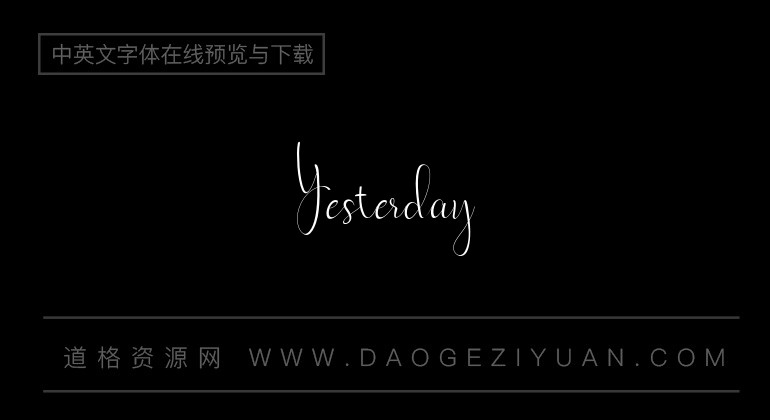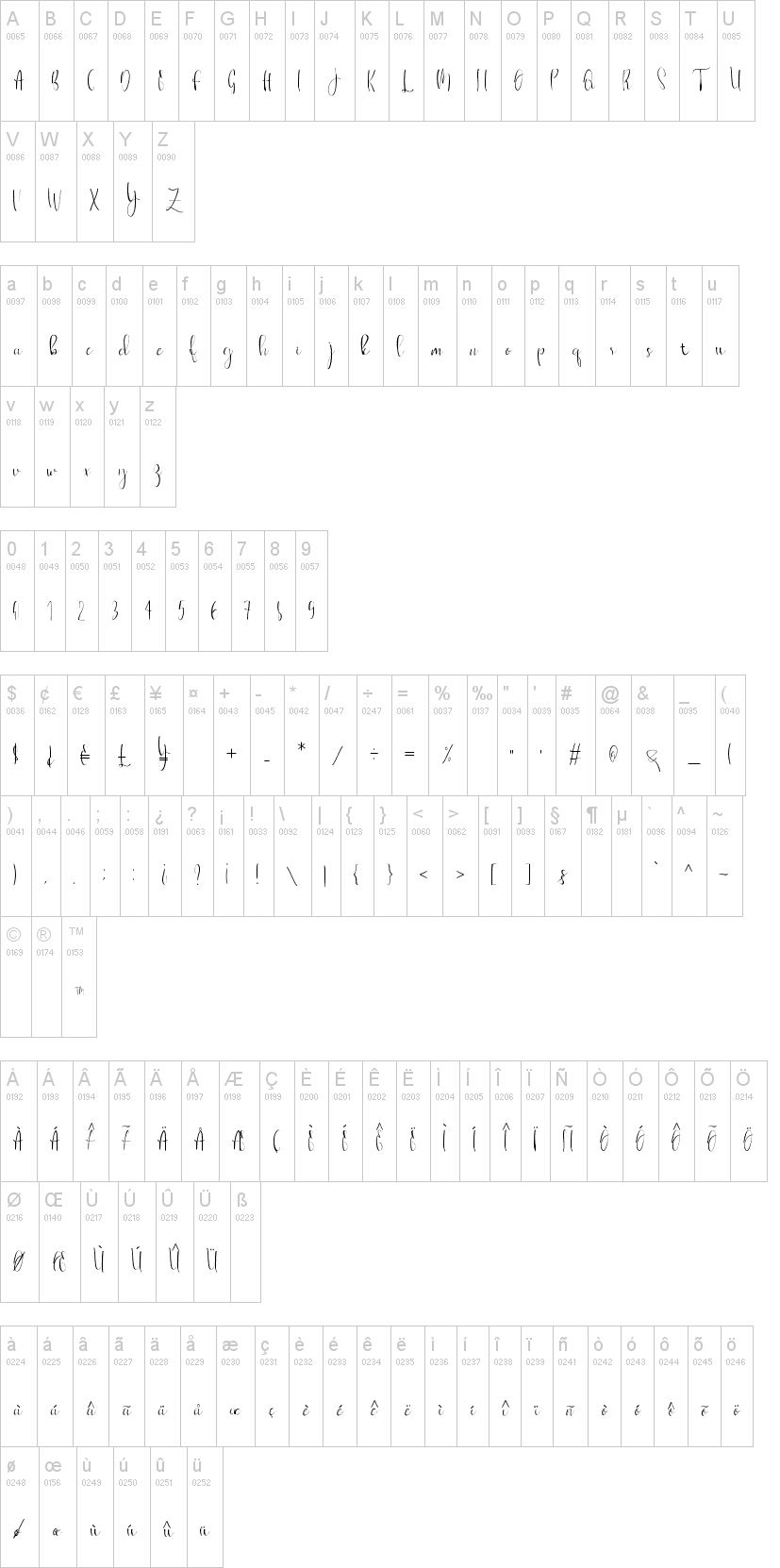
Yesterday
Yesterday 是一款设计师的手写字体,它拥有温暖的感觉,柔和的线条,清晰的字形,以及多变的魅力。它可以用于各种不同的设计,从卡片到海报,从网站到插图,都能够表现出独特的气质。它可以提供有趣的文字效果,也可以用作大胆的标题或句子,以添加更多的惊喜。
Yesterday是一款非常不错的手写艺术字体,具有很好的视觉感,适合于文化类的宣传设计、商业类品牌的广告和产品包装设计以及个性化文字排版等较多场景。